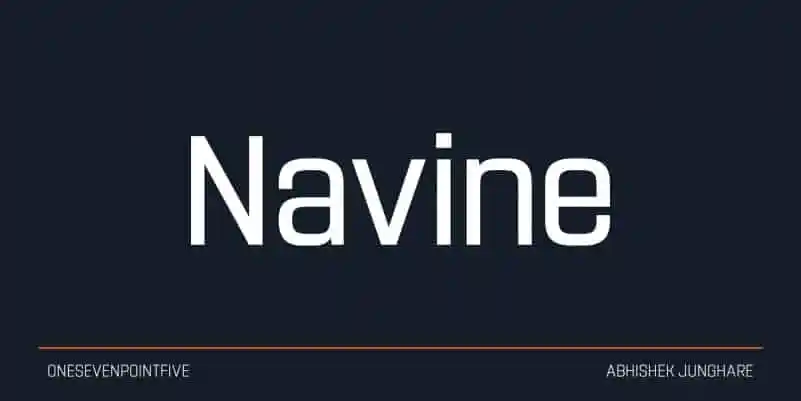
Navine – Sans Serif Font Demo – Download Grátis
A Navine é uma tipografia de sans serif que oferece uma experiência atraente para designers visuais. Com três larguras distintas e 9 itálicos para cada, essa fonte proporciona flexibilidade semelhante à de um tipo comum, mas com a modernidade de um estilo sinóptico. O designer onesevenpointfive criou a Navine para ser uma fonte versátil que combina facilmente em projetos criativos e arrojados. O maior marco da fonte é sua capacidade única de incorporar recursos OpenType avançados, incluindo alternativas de caracteres e parais em pares de espaçamento. Além disso, Navine traz superiores e inferiores personalizados, tornando-o ainda mais sofisticado para os projetos que exigem um toque acentuado ou especial. Com uma abordagem puramente informativa e convidativa, a fonte é perfeita para designers que buscam combinar estilo moderno com recursos avançados. A Navine não apenas oferece flexibilidade nos formatos, mas também permite um design mais detalhado e sofisticado em seus projetos visuais. Esta tipografia de sans serif apresenta-se como uma excelente escolha para quem busca fontes de qualidade que se adapta perfeitamente a diferentes estilos de design.